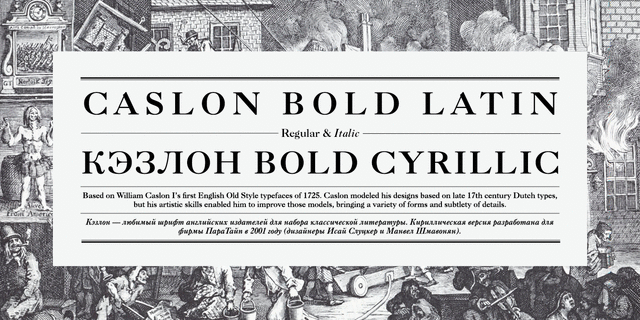
Версия фирмы Bitstream шрифта Caslon Bold фирмы American Typefounders, 1905. Шрифт разработан на основе первой английской антиквы старого стиля знаменитого типографа Уильяма Кэзлона I, выпущенной в 1725 году. Кэзлон создавал свои шрифты по образцу голландских шрифтов XVII века, но его художественное мастерство позволило ему улучшить качество своих шрифтов, привнеся в них разнообразие форм и искусность деталей. В шрифтах Кэзлона основные штрихи тяжелее, чем в большинстве антикв старого стиля, засечки толще и несколько коренастее. Наклон курсивных знаков колеблется.В целом текст, набранный Кэзлоном, выглядит привлекательно и хорошо читается. Кэзлон - любимый шрифт английских издателей для набора классической литературы. Кириллическая версия разработана для фирмы ПараТайп в 2001 году (дизайнеры Исай Слуцкер и Манвел Шмавонян).
Ассоциации c начертанием Caslon Bold NormalКачества и характер:
благородный, консервативный, традиционный, классический, повествовательный, художественный, образованный, острый, мастерский, точный, аристократичный, элитный, правильный, статичный, комильфо, пафосный, исторический, гуманитарный, гордый, джентльменский
библиотека, искусство, музей, литература, эстетика, проза, поэзия, музыка, детектив, геральдика, чай, образование, комильфо, обед, ужин, замок, концерт Стилистика: